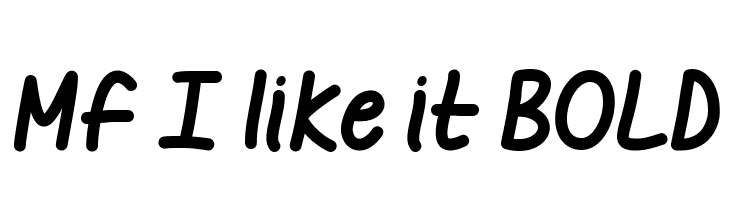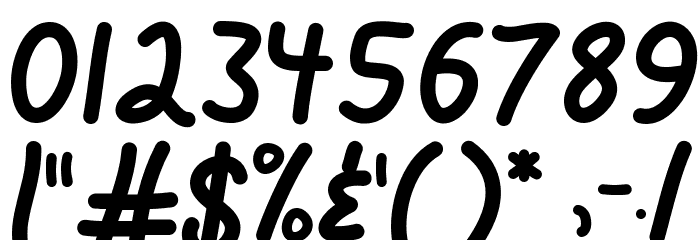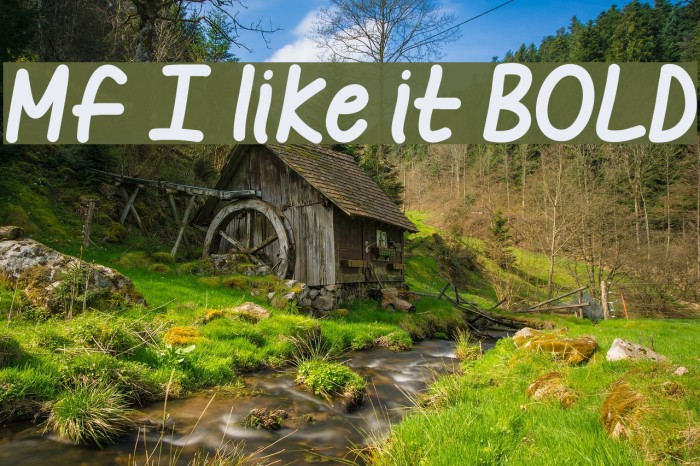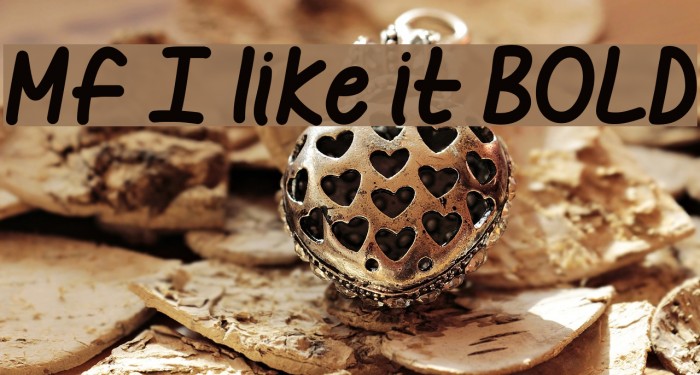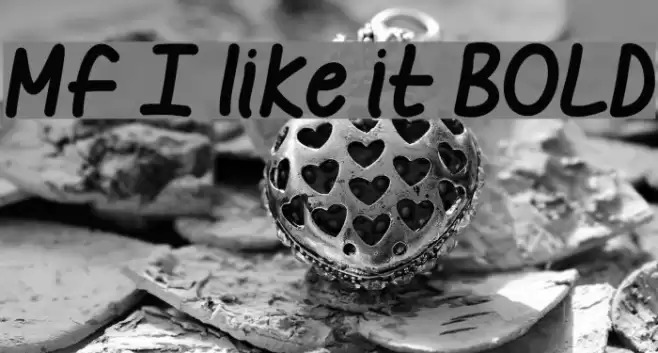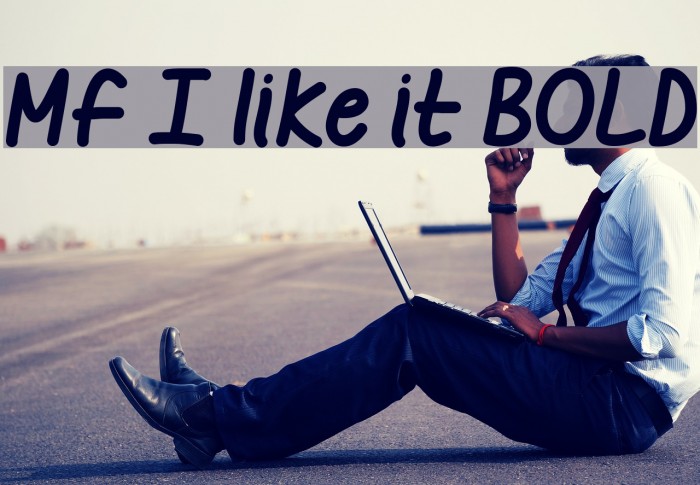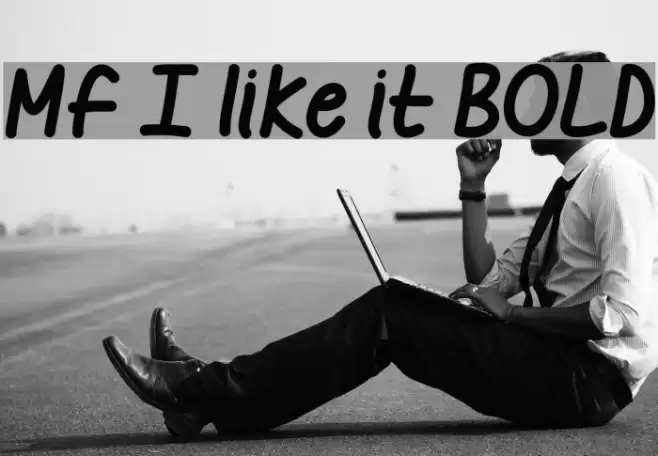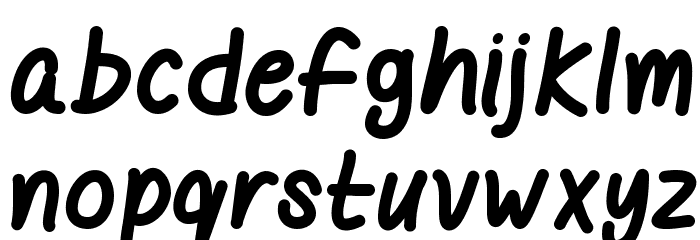
Mf I like it BOLD Font
| Gesamtstil | Playful, Casual |
| Anwendungsfall | Headlines, Invitations, Posters |
| Vorgeschlagene Projekte | Ideal for invitations, posters, branding materials, and any project needing a personal touch. |